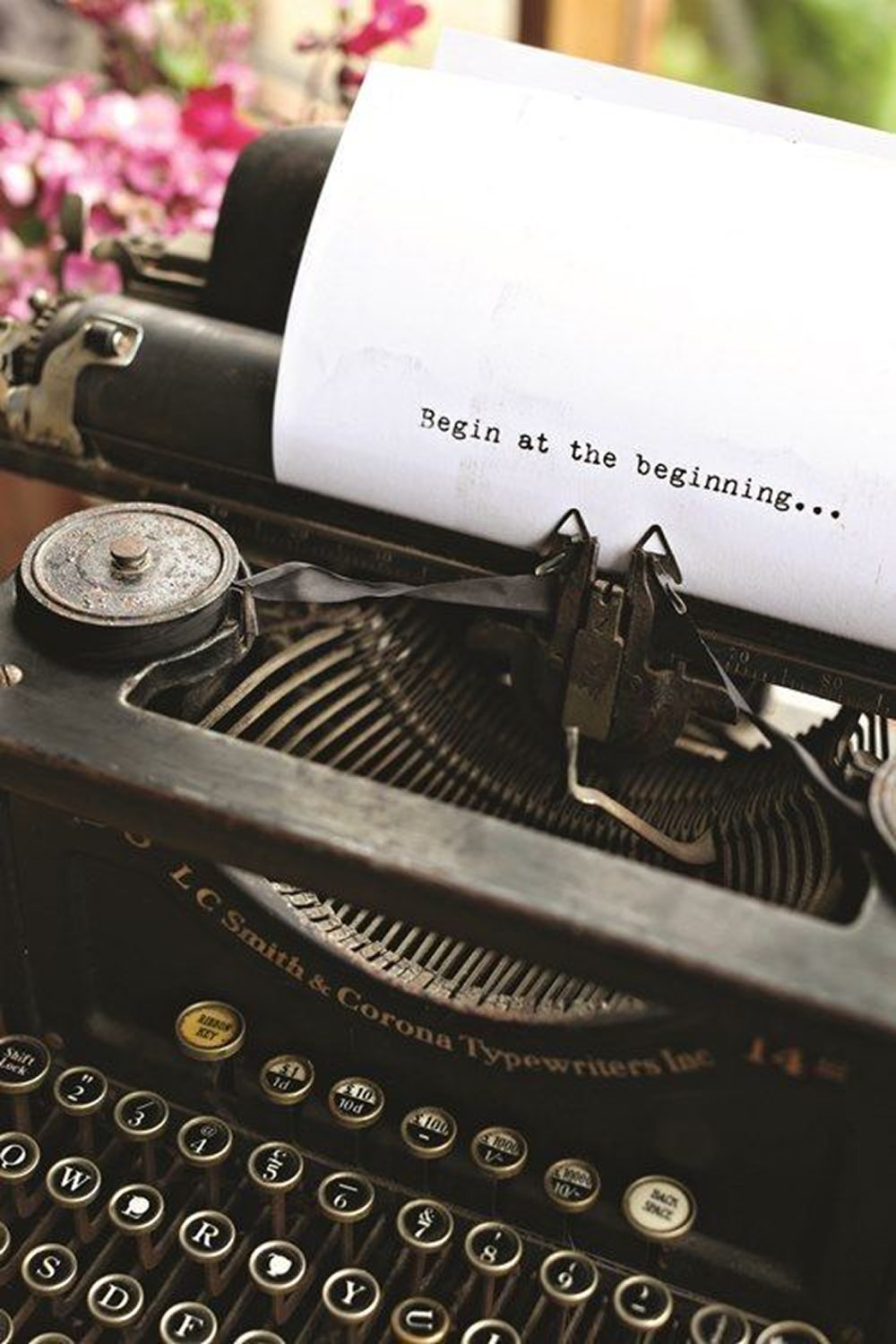
Типографика — это не просто шрифт
Типографика — это не про «поставим Inter, потому что красиво».
Это не выбор между шрифтами из папки «Favorites».
Это, по сути, второй голос бренда — наряду с логотипом.
✍️ Шрифт — это буквы.
Типографика — это как они говорят. Как дышат. Как звучат в твоей голове.
Можно взять один и тот же шрифт и выдать:
— скучный корпоратив,
— модный бренд,
— или «тут у нас презентация по биологии».
💬 В типографике работает всё:
— кегль (где поставить акцент),
— межбуквенное (дышит текст или задыхается),
— ритм строк (медленно или как автоматная очередь),
— заглавные/прописные (авторитет или диалог),
— выравнивание, плотность, воздух.
Типографика умеет передавать эмоцию даже без иллюстрации.
Это когда ты читаешь заголовок — и уже понимаешь, что тебе хотят сказать, даже до смысла.
Сильная типографика может быть айдентикой сама по себе.
📌 Если ты всё ещё выбираешь «шрифт, чтобы не резал глаз»,
а потом бросаешь всё на автопилот — ты просто теряешь инструмент влияния.
Визуально сильный бренд — это не только про логотип.
Это про то, как текст стал характером.